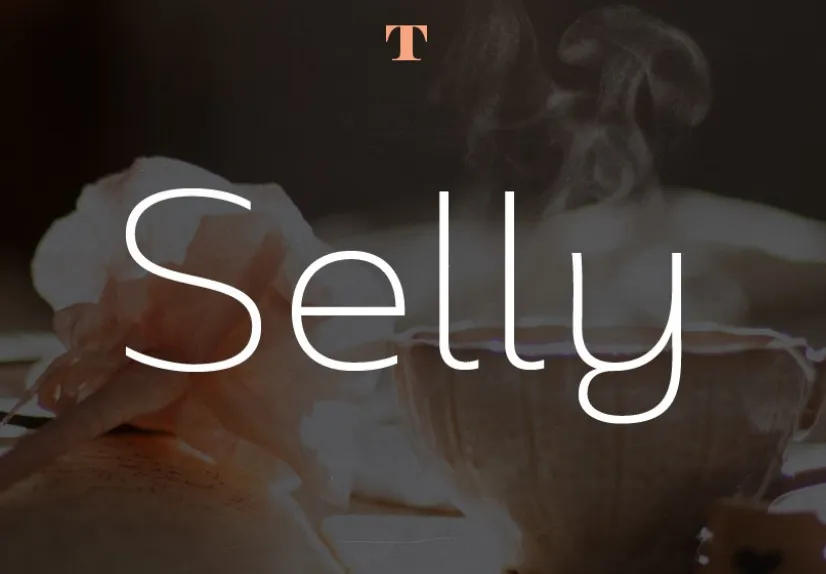
A Selly é uma fonte de tipo casual que foi projetada para qualquer uso exibicional. Suas linhas leves e curvas suaves fazem dela uma escolha perfeita para ambientes digitais, como sites ou banners, bem como para identidades corporativas e desenho editorial. Seu design limpo e elegante a torna fácil de combinar com outros tipos, garantindo um resultado arrojado e moderno em qualquer projeto. A Selly é uma opção perfeita para designers que buscam uma fonte leve e versátil para trabalhos digitais ou impressos. Compostas cuidadosamente para uma aparência atraente e de fácil legibilidade, as linhas da Selly se adaptam perfeitamente em qualquer projeto, desde pequenos detalhes até grandes formatos, garantindo que sua mensagem seja transmitida com clareza e estilo.